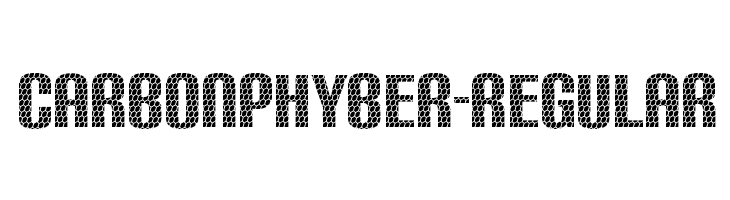
A bold, italicized font with a futuristic halftone effect and tight spacing.
A bold, geometric font with outlined characters for a modern, impactful look.
A bold, flowing script font with elegant, dynamic strokes.
A bold, geometric font with an industrial, block-like design.
A high-contrast, elegant font with a modern and sophisticated style.
An elegant, cursive script with ornate flourishes and smooth curves.
A bold, artistic font with a hand-drawn, textured style.
A bold, futuristic font with a geometric, three-dimensional style.
A dynamic, handwritten font with fluid and expressive strokes.
A lively and playful script font with smooth, flowing curves.
A bold, italicized font with a futuristic halftone effect and dynamic style.
A modern font combining geometric uppercase with cursive lowercase elements.
A bold, geometric font with a futuristic and angular design.
A bold, italic typeface with a dynamic and modern style.
An elegant, decorative script font with intricate swirls and artistic flourishes.
A bold, playful font with organic, blob-like shapes and a whimsical style.
A cryptic, geometric font with a mysterious, cipher-like appearance.
A bold, condensed font with a modern industrial style and high contrast.
A bold, outlined font with a vintage yet modern style.
A modern, geometric font with sharp angles and smooth curves, ideal for contemporary designs.
A dynamic handwritten font with fluid, energetic strokes.
An elegant script font with intricate swirls, perfect for formal invitations.
A bold, Gothic blackletter font with high contrast and ornate detailing.
A futuristic, angular font with bold, italicized characters and geometric shapes.
A hand-drawn, sketch-like font with an edgy and artistic style.
Invalid font rendering; only placeholder boxes are visible.
A sophisticated cursive script with elegant, flowing lines and ornate flourishes.
A playful, handwritten-style font with smooth curves and a friendly vibe.
A festive collection of holiday-themed dingbats featuring ornaments, gifts, and more.
A whimsical font with letters as cat and dog faces, perfect for playful designs.
A dynamic cursive script font with fluid, interconnected strokes and a lively appearance.
A playful, cursive font with bold strokes and a whimsical style.
A geometric, futuristic font with bold, circular shapes and unique cut-out patterns.
A bold, handwritten font with a playful and energetic style.
An elegant, flowing script font with modern, decorative elements.